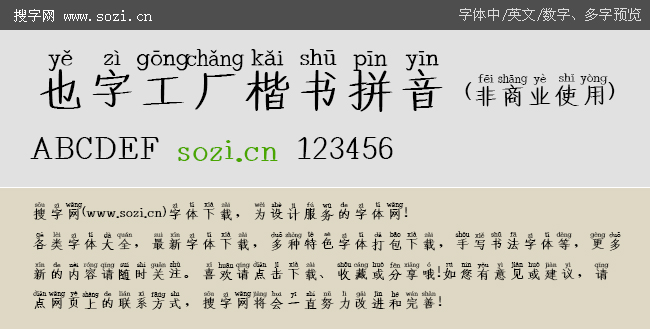
也字工廠楷書拼音
搜字網(wǎng)給大家提供一款也字工廠楷書拼音(非商業(yè)使用)中文字體下載,也字工廠楷書拼音是一款楷體字體,字體簡(jiǎn)潔大方,字形端正自然。并配有漢語(yǔ)拼音。具有很好的視覺效果。適合應(yīng)用于童書設(shè)計(jì)、兒童海報(bào)設(shè)計(jì)、網(wǎng)頁(yè)設(shè)計(jì)、包裝設(shè)計(jì)等應(yīng)用(此字體為個(gè)人非商用版,商用可以聯(lián)系:官方網(wǎng)址:https://yefont.com/home,聯(lián)系方式:13798980448)。